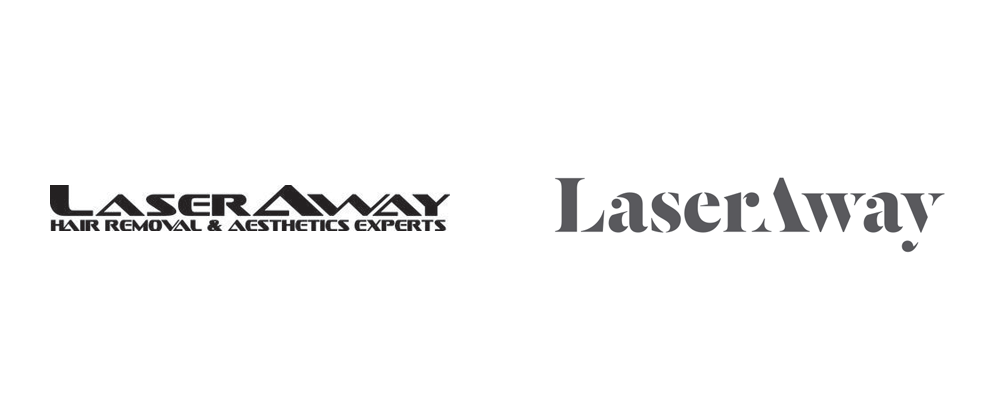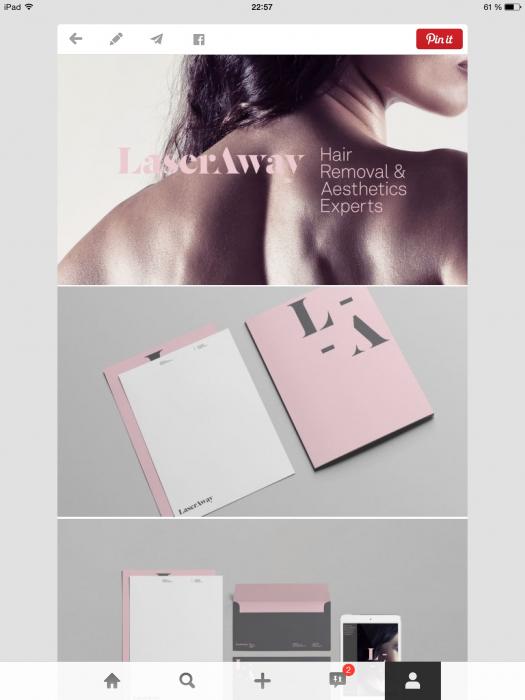
Vom "laseraway"
die fehlende teile im schriftzug sind natürlich handgemacht.
würde man denken, aber nein: es ist eine existierende schriftart, und zwar die dala floda. nur das ›A‹ haben sie minimal angepasst (querstrich entfernt).
sowohl die minion aus deiner anderen frage als auch die dala floda habe ich ›einfach‹ erkannt. bei der minion war es das ›R‹, an der ich sie erkannt habe (nachdem ich die abbildung in photoshop um 300% vergrößert hatte, daher die bitte im anderen thema, gleich höher aufgelöste abbildungen zur verfügung zu stellen). die dala floda wiederum ist so ein bunter vogel, dass ich nicht lange nachdenken musste. außerdem bin ich ein fan von commercial type – oder sagen wir mal: ein bewunderer aus der ferne. ich habe noch nie was von denen lizenziert, aber sie haben viele sachen, die mich ansprechen. dein glück dieses mal! :ilovetype:
Die Geschichte dazu gibt es hier: http://dia.tv/laseraway/